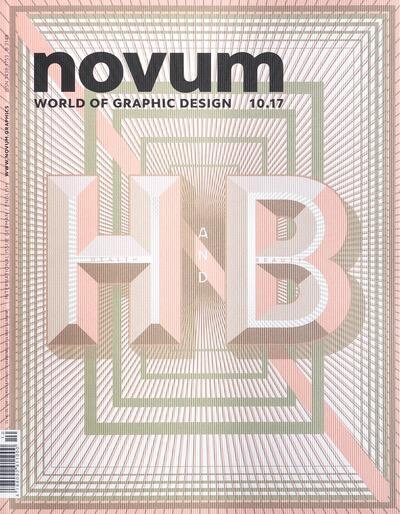
Die Novum war ein Fachmagazin, das sich den Themenschwerpunkten Grafik- und Kommunikationsdesign widmete. Das am Ende in München beim »Stiebner Verlag« erschienene Magazin geht auf das seit 1924 in Berlin herausgegebene Heft »Gebrauchsgraphik« zurück.
In Deutschland trugen vor allem die Veröffentlichungen des Vereins der Plakatfreunde unter dem Namen »Das Plakat«, zum Aufstieg der Designpresse bei. Von 1910 bis zu seiner Schließung 1922 veröffentlichte der Verein ein vierzehntägig erscheinendes Journal mit einer Auflage, die sich von anfangs zweihundert auf mehr als fünftausend Exemplare steigerte, und ebnete so den Weg für das erste zweisprachige Magazin für Grafikdesign (englisch/deutsch), das ab 1924 unter dem Namen »Gebrauchsgraphik« im Berliner Verlag Phönix Druck herausgegeben wurde.
Innerhalb von zwei Jahren hatte sich das Heft zu einer »Monatsschrift zur Förderung künstlerischer Reklame« gemausert, so der Gründer Prof. K.H. Frenzel, der neben der Redaktionsarbeit alljährliche Kritiken zur deutschen Plakatkunst heraus gab und sich vor allem auf die Experimentierfreude des Bauhauses und anderer Protagonisten der Avantgarde konzentierte. Dabei legte er grundsätzlich Wert auf hohe Qualität in angewandter Grafik. Gleichzeitig hielt der Gründervater des BDG (Bund Deutscher Gebrauchsgraphiker) Verbindungen zu Fachleuten in ganz Europa und den USA aufrecht. So wurden Leser des Magazins schon damals über weltweite Entwicklungen auf dem laufenden gehalten.
Die Zeitschrift porträtierte Konstruktivisten wie den Russen El Lissitzky ebenso wie die Londoner Aktivitäten des US-Designers McKnight Kauffer. Und als The Book Service Company of New York den Vertrieb in den USA übernahm, stand der internationale Erfolg des Magazins fest. Mit dem Untertitel »International Advertising Art« überlebte es dann zwar die ersten Jahre des Dritten Reiches, musste jedoch aufgrund des Zweiten Weltkrieges und der schwierigen Nachkriegsjahre ab 1944 die Druckerpressen für sechs Jahre stoppen.
In den ersten Jahrzehnten des 20. Jahrhunderts hatte sich Gebrauchsgraphik aber längst zu einem kreativen Prototypen für die Design-Magazine der Moderne entwickelt, darunter zum Beispiel Graphis, Communication Arts oder Idea. Und dies, obwohl sich die Zeitschrift seit ihrer Münchner Neugründung durch Eberhard Hölscher (Bruckmann Verlag) im Jahre 1950 immer wieder neu erfunden hat.
Die Veränderungen in der Welt der visuellen Kommunikation zeigen sich deutlich anhand älterer Ausgaben. Während in den späten fünfziger Jahren noch Illustrationen das Erscheinungsbild prägten und Futura als Hausschrift verwendet wurde, gewannen Markenbildung und Corporate Design in den Sechzigern zunehmend an Bedeutung und die Zeitschrift verwendete ab 1966 die Schrift Helvetica.
In den siebziger Jahren richtete sich der Fokus auf pädagogische Sujets und im Anschluss an die Umstellung auf Fotosatz (9/79) erschien mit Univers ein visuell schlichtes und funktionales Layout, das den redaktionellen und zunehmend revolutionären Inhalten über Post-Modernismus und Computer-Design zu widersprechen schien. So standen in novum 8/84 die Plakate des provokativen Meisters Alain Le Quernec dem digitalen Bilderumsturz aus Japan gegenüber.
Verschiedene Design-Trends der achtziger Jahre führten zu einer Reihe von parallellaufenden Stilwandlungen und das Erscheinungsbild des Magazins änderte sich im letzten Jahrzehnt des auslaufenden Jahrtausends dreimal. Der komprimierten Old-Face-Schrift folgten erst Otl Aichers Rotis und schließlich Garamond. In dieser Zeit erfolgte auch ein Generationenwechsel in der novum-Redaktion und die Zeitschrift, die zuvor viersprachig (Deutsch, Englisch, Französisch, Spanisch) erschien, wurde auf die Sprachen Deutsch und Englisch reduziert.
Untertitel: World of Graphic Design